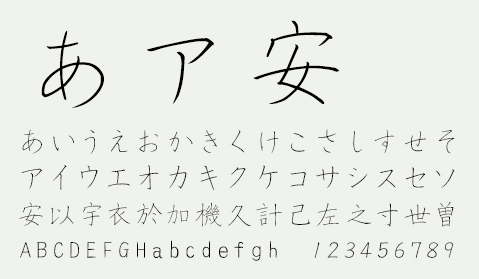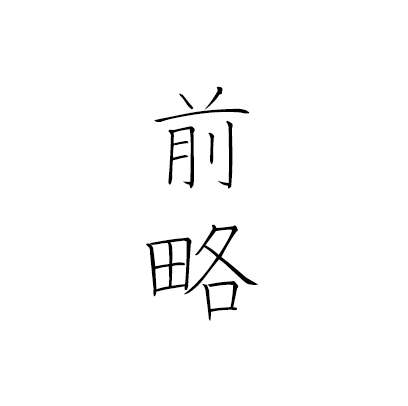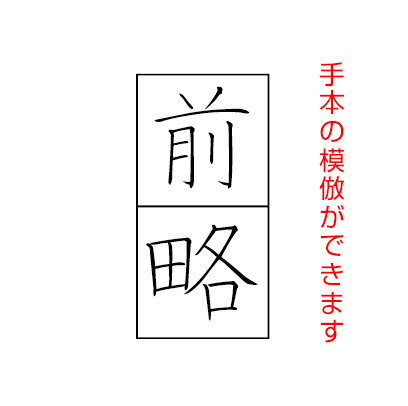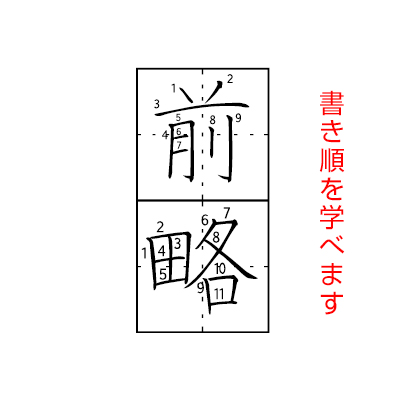
文科省の学習指導要領に準拠しつつ、
唐の大家を参考とした美しい字形のフォントです
ウェイト見本
- NSK白洲ペン字楷書フォント/w1
- NSK白洲ペン字楷書フォント/w3
- NSK白洲ペン字楷書フォント/w6
NSK白洲ペン字楷書手本セット
フォント別特徴
ひらがな・カタカナ・漢字を使い分けることで、より美しい文字バランスを実現できます
| NSK⽩洲ペン字楷書 フォント(標準形) |
升目付き | 外枠付き | 書き順付き (小学6年生迄の学習漢字) |
学びたい文字を入力・印刷するだけでオリジナルのペン字手本を作成できます